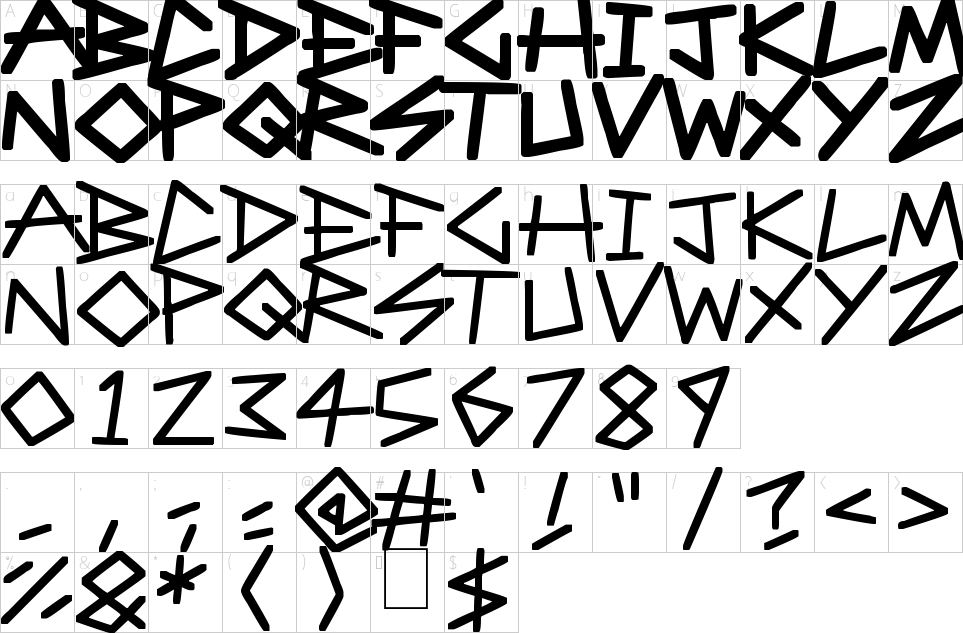
A Angular Anarchy font é um recurso gráfico criado para os amantes de design e programadores que buscam uma fonte atemporal e distinta para seus projetos. Desenhada pelo designer Darrell Flood, essa fonte traz uma combinação única de simplicidade e poder, ideal para projetos que exigem uma paixão única e uma personalização forte. Seja você um designer gráfico, um desenvolvedor ou até mesmo um criador de conteúdo, a Angular Anarchy font pode complementar sua paleta de recursos, dando um toque distinto e moderno a qualquer projeto. Com mais de 2.685 downloads, essa font vem sendo apreciada por designers de todo o mundo que buscam uma maneira única de estilizar seus materiais. Instale-a hoje e dê um novo impulso à sua paleta de recursos gráficos.